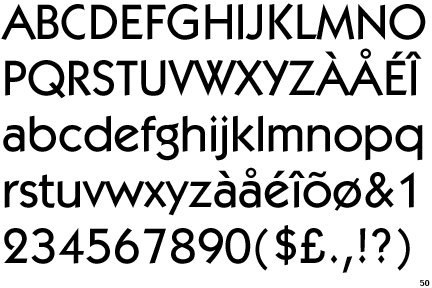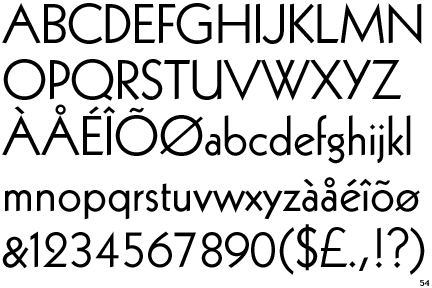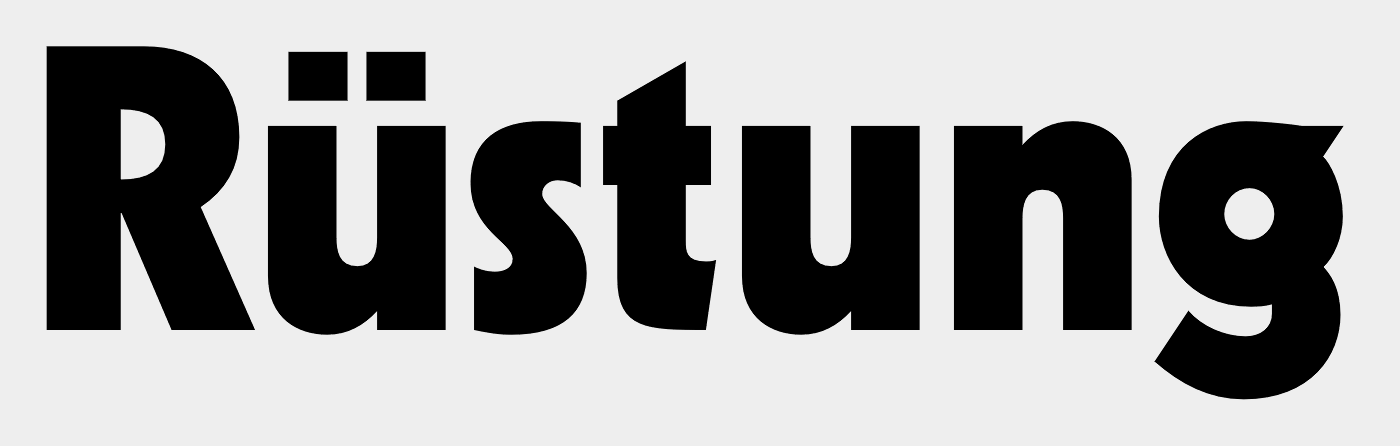
[Mitglied phfi…] Geschrieben September 18, 2015 Teilen Geschrieben September 18, 2015 Sehr geehrte Experten, sicherlich keine sonderlich außergewöhnliche Schrift für die Zeit, aber ich finde einfach nichts dazu. Als völlig Unwissender sieht sie für mich aus wie eine Art Gill mit Futura-mäßigem M und W, eckigen Punkten und "gekipptem" e. Die Beispiele sind alle Spiegel-Titel (Zeitraum 72-82), die sie verwendeten. Vielen Dank im Voraus! Link zu diesem Kommentar
Beste Antwort [Mitglied 8966…] Geschrieben September 18, 2015 Beste Antwort Teilen Geschrieben September 18, 2015 bei MyFonts herunterladen Sieht man am g und am schrägen e Link zu diesem Kommentar
[Mitglied Gizz…] Geschrieben September 18, 2015 Teilen Geschrieben September 18, 2015 is similar to : https://www.myfonts.com/fonts/tilde/geometr-231/heavy/ (but the timeframe is wrong) Link zu diesem Kommentar
[Mitglied phfi…] Geschrieben September 18, 2015 Themen-Ersteller Teilen Geschrieben September 18, 2015 Vielen Dank! Ist das also nur meine falsche Wahrnehmung, dass man sie in den 60ern kaum verwendete oder gibt es einen Grund, warum die scheinbar 1927 veröffentlichte Schrift mit den 70ern diesen Popularitätszuwachs verzeichnen konnte? Link zu diesem Kommentar
[Mitglied Uwe…] Geschrieben September 18, 2015 Teilen Geschrieben September 18, 2015 (bearbeitet) Hallo, Vielen Dank! Ist das also nur meine falsche Wahrnehmung, dass man sie in den 60ern kaum verwendete oder gibt es einen Grund, warum die scheinbar 1927 veröffentlichte Schrift mit den 70ern diesen Popularitätszuwachs verzeichnen konnte? In den 1970ern, genauer genommen 1975, kam das Remake mit der stark vergrößerten x-Höhe von Victor Carouso bei ITC raus. Das scheint damals gut vermarktet worden zu sein. ITC Kabel Medium Designers: Rudolf Koch and Victor Caruso Year: 1925, 1975, 1988 Copyright: ITC Publishers: Adobe and ITC Hier mal die Originalkabel von Rudolf Koch aus dem Jahr 1927 mit der wesentlich niedrigeren x-Höhe. MfG Kabel One of the first geometric sans-serif designs directly influenced by the Bauhaus movement, and named in honor of the laying of the first trans-Atlantic telephone cable. Designer: Rudolf Koch Year: 1927, 1991 Copyright: Linotype Publishers: Adobe and Linotype Die Original-Kabel ist wesentlich seltender zu finden. Deren geringe x-Höhe erscheint wohl vielen Betrachtern unzeitgemäß und gewöhnungsbedürftig. bearbeitet September 18, 2015 von Uwe Borchert 1 Link zu diesem Kommentar